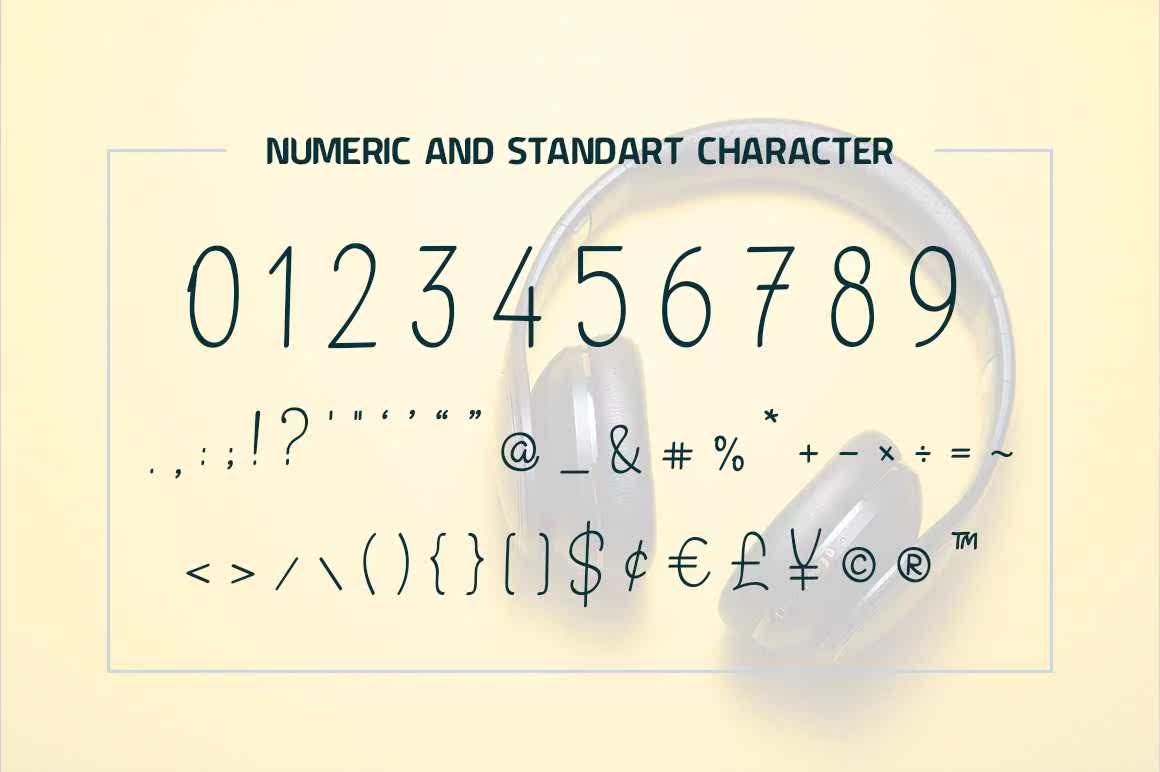
BadriyatUnscripts是一款具有基线、平滑线、经典和有趣触感特征的时尚字体。可用于各种用途。例如标题、签名、徽标、海报、t恤、标牌、标签、婚礼宣传、徽章等。BadriyatUnscripts是一款具有基线、平滑线、图案和图案特征的时尚字体,经典互动触控。可用于各种用途。如标题、签名、徽标、海报、t恤、标牌、标签、婚礼活动、徽章等。